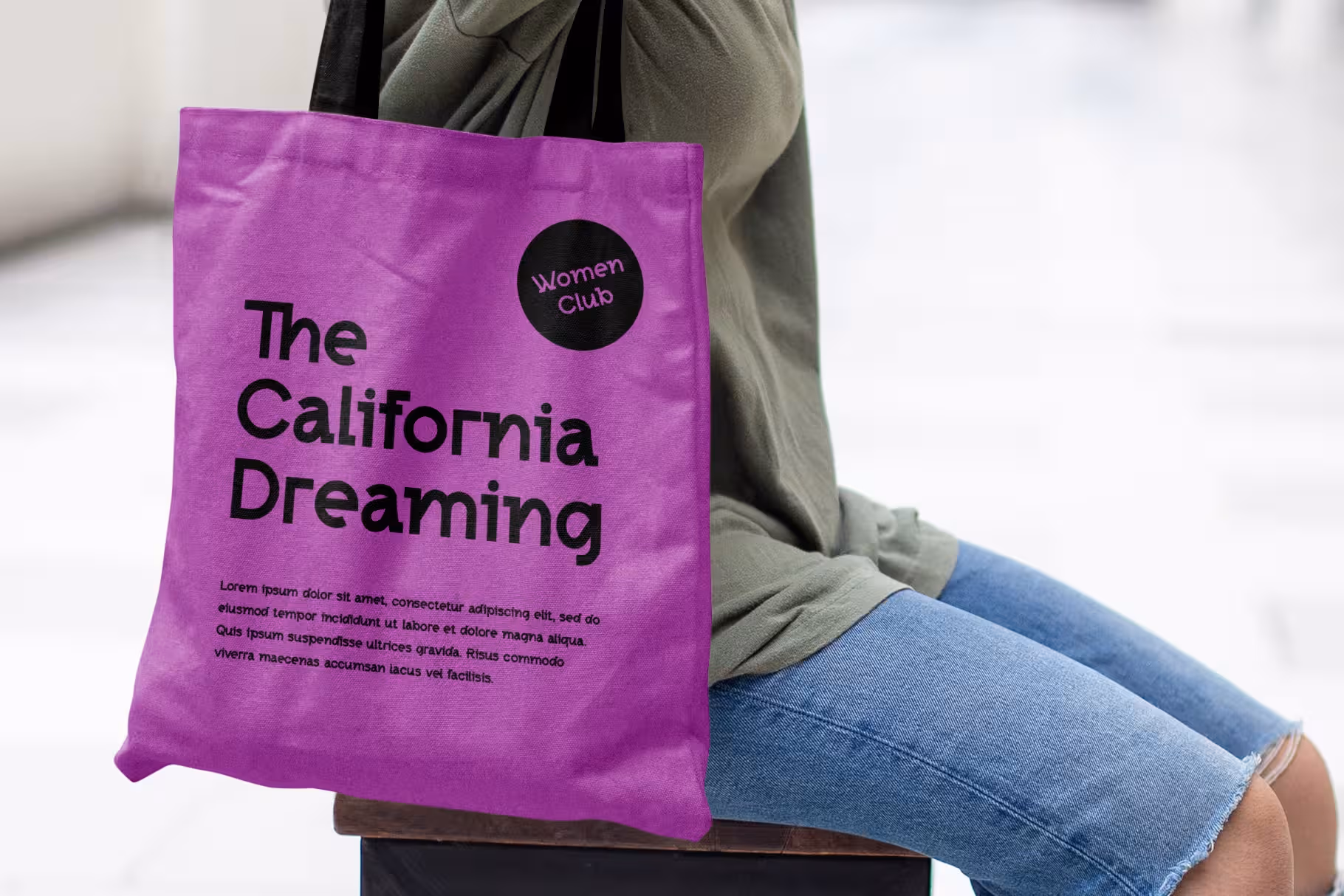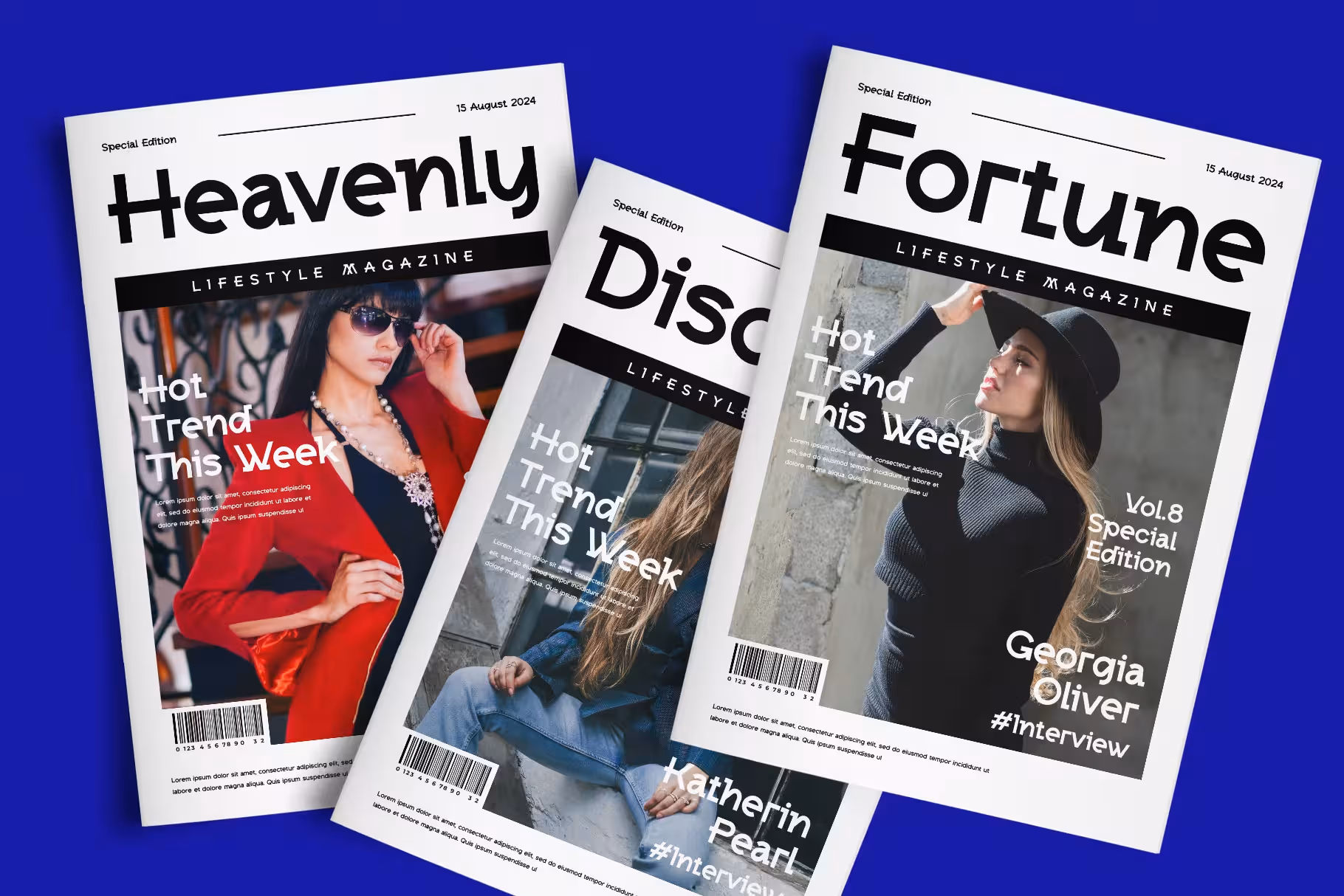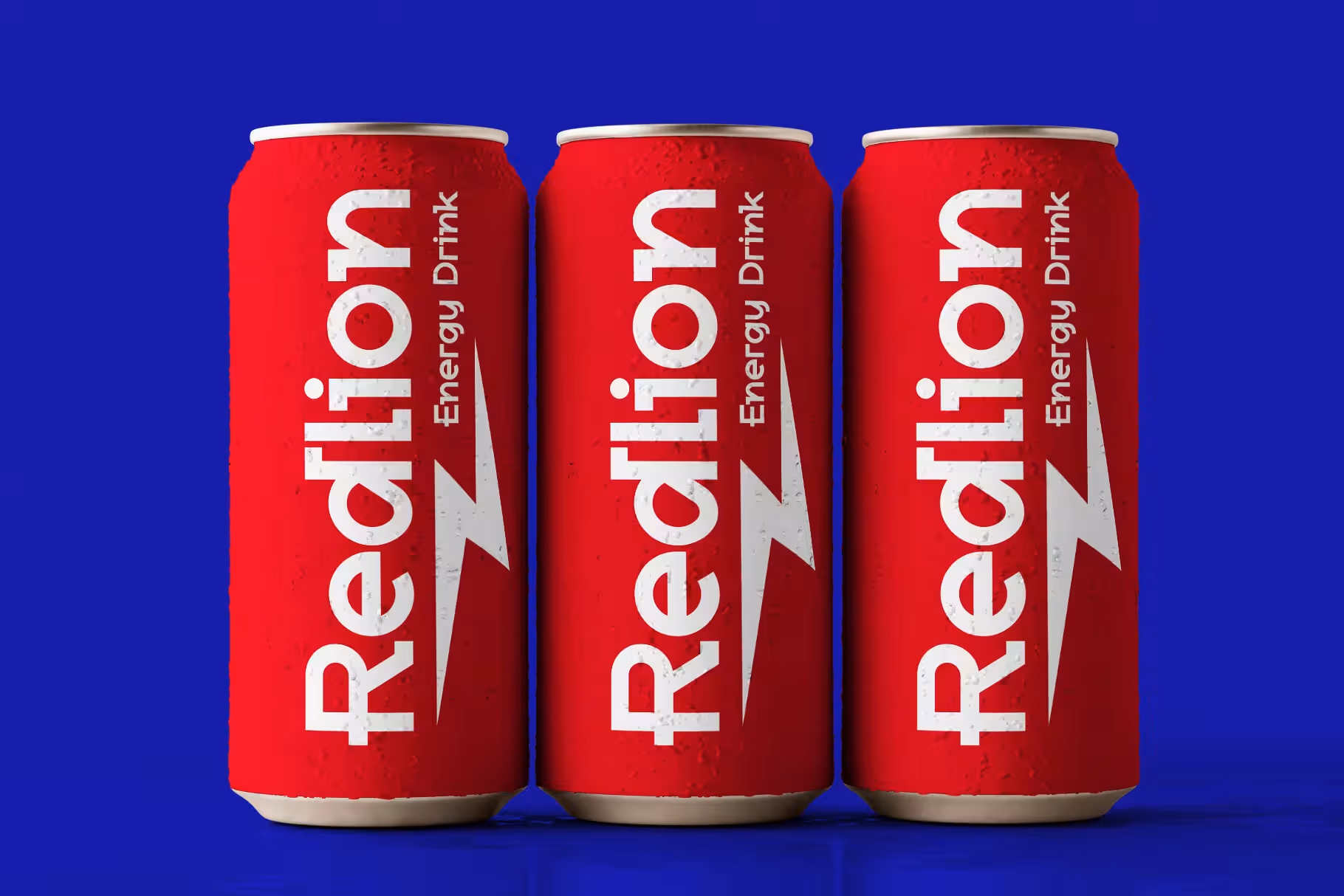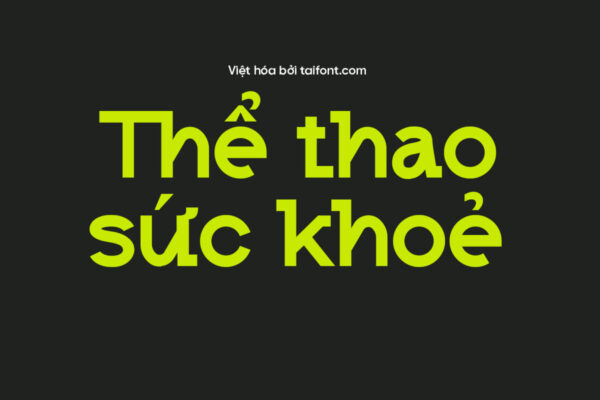
Giới thiệu về Font TF Bendagi Việt hóa
TF Bendagi Việt hóa là một font chữ độc đáo, kết hợp giữa phong cách không chân (sans-serif) hiện đại và yếu tố trang trí mạnh mẽ, tạo nên vẻ ngoài đầy cá tính, năng động và ấn tượng. Font này toát lên sự mạnh mẽ, tốc độ và một chút táo bạo, lý tưởng để tạo điểm nhấn nổi bật và truyền tải thông điệp một cách dứt khoát.
Với đặc điểm thiết kế độc đáo và khả năng gợi cảm xúc mạnh mẽ, Bendagi là lựa chọn hoàn hảo cho các ấn phẩm trong lĩnh vực thể thao, công nghệ và in ấn:
- Thiết kế thể thao: Hoàn hảo cho các poster, banner quảng cáo phòng gym, trung tâm thể hình, sự kiện thể thao, hoặc các thương hiệu liên quan đến thể thao như trang phục, dụng cụ, hoặc phụ kiện. Font này giúp tạo không khí sôi động, cạnh tranh và mạnh mẽ, thúc đẩy tinh thần chiến thắng.
- In ấn: Đảm bảo khả năng đọc tốt ngay cả ở kích thước lớn, và tạo hiệu ứng thị giác mạnh mẽ khi in trên các chất liệu khác nhau như áo thun, biểu ngữ, hoặc các sản phẩm quảng cáo. Sự rõ ràng và nổi bật của font giúp thông điệp truyền tải hiệu quả.
- Thiết kế tạp chí: Lý tưởng để sử dụng cho các tiêu đề chính, lời dẫn hoặc các bài viết đặc biệt trong các tạp chí về thể thao, công nghệ, hoặc các ấn phẩm cần sự mạnh mẽ và hiện đại.
- Thiết kế thương hiệu: Phù hợp cho logo hoặc bộ nhận diện thương hiệu muốn truyền tải sự năng động, đột phá và uy tín.
Với TF Bendagi Việt hóa, bạn có thể dễ dàng thổi hồn mạnh mẽ, năng lượng và sự độc đáo vào các thiết kế, tạo ra những sản phẩm không chỉ đẹp mắt mà còn cực kỳ ấn tượng và có khả năng thu hút sự chú ý tối đa.
Font Việt hóa TF Bendagi